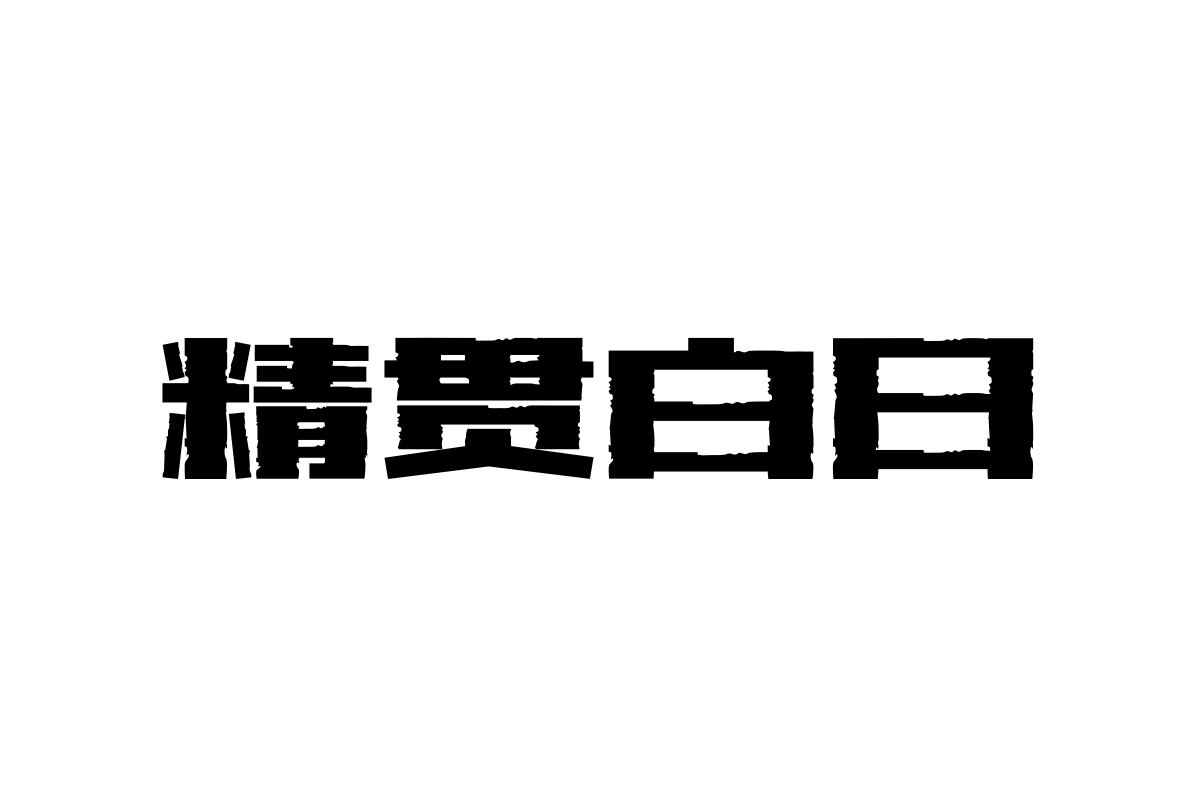
上首暗格体是一款具有独特风格的字体,它的特点是将汉字的笔画进行重新组合和排列,形成了一种独特的视觉感受。这种字体的特点是笔画粗细不一,有的笔画较粗,有的笔画较细,给人一种强烈的视觉冲击感。同时,这种字体的字形也较为复杂,需要一定的学习才能掌握。总的来说,上首暗格体是一款非常独特且具有挑战性的字体,适合喜欢追求个性和创新的用户使用。